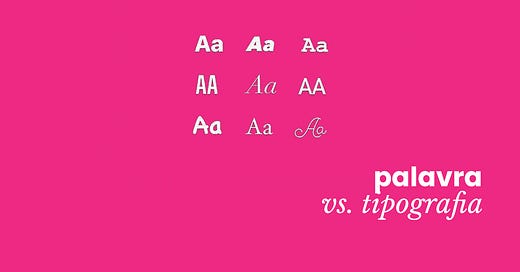
#63 palavra vs. tipografia
quando dois aspectos essenciais do texto são tensionados | tempo de leitura: 7 minutos
oie, seja bem vinde a mais uma edição da makers gonna make. a semente da edição de hoje foi plantada na minha cabeça em 2017, quando participei de um curso de escrita criativa e o professor contou uma anedota meio controversa sobre o design de um livro pela editora Cosac Naify. a história voltou num estalo na semana passada enquanto eu lia Design Gráfico: Uma história concisa, de Richard Hollis; e a partir daí fui ligando os pontos. o que está envolvido na relação - às vezes tensa - entre palavra e tipografia?
🔡 Tipografia para reforçar a mensagem
Estamos acostumados a usar sinais visuais para indicar nuances que achamos que faltam nas nossas palavras quando digitamos na internet: os emojis são o maior exemplo disso. Mas com a comunicação acontecendo cada vez mais através de layouts de posts ou texto aplicado sobre vídeo - e menos em textos corridos, como esse - isso se estendeu também para o campo da tipografia (não que nesse texto não haja tipografia, mas eu certamente conto com menos recursos no Substack e no e-mail do que em outros espaços virtuais).
Pode parecer bobo, mas eu acho que nos últimos anos os stories do Instagram se tornaram um espaço de exploração tipográfica. Cada vez que uma pessoa, designer ou não, posta uma foto acompanhada de texto, ela pode escolher entre as nove opções de tipografia que o Instagram oferece, além de algumas opções de animação (!) e infinitas possibilidades de cores. Já vi muita gente clicar em todas as opções e decidir qual prefere no feeling, mas esse não deixa de ser um trabalho de adequação de tom tipográfico para e mensagem textual.
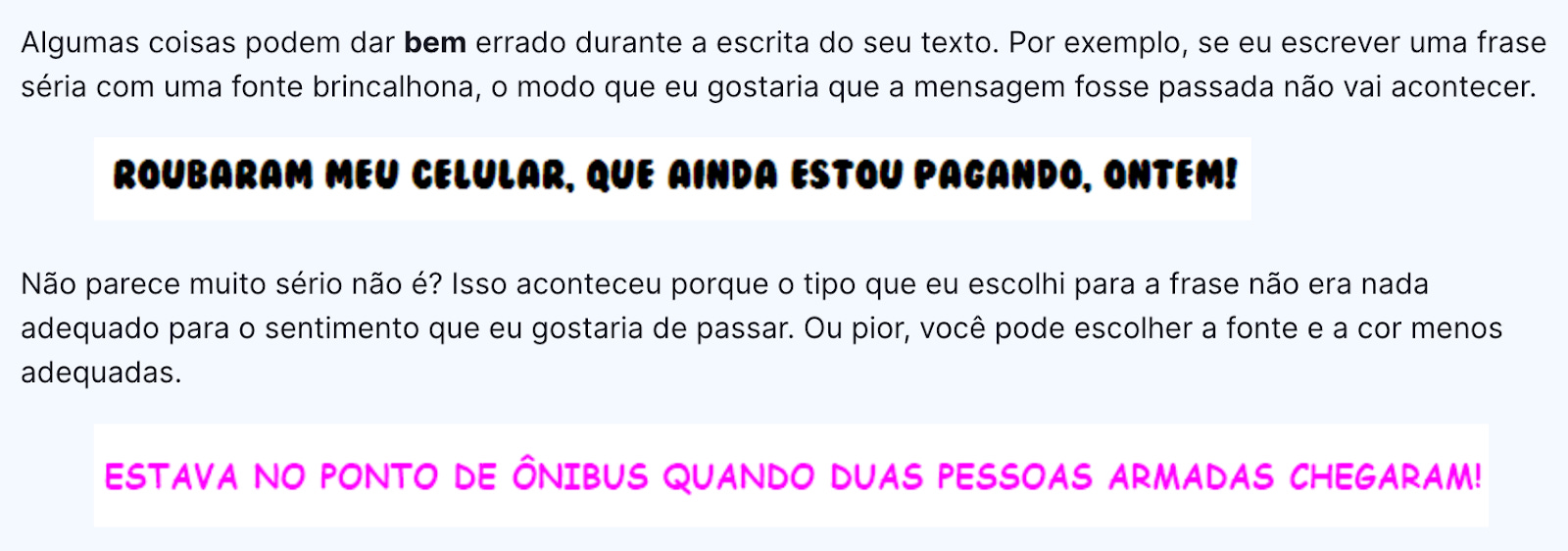
Essa relação entre forma e conteúdo não é recente: a formação clássica em design gráfico nos ensina que a aparência de uma palavra tem tanto ou mais força quanto o seu significado. Um argumento comum para engrandecer os feitos tipográficos é que a tipografia não é só importante, mas necessária para suprir uma espécie de deficiência da palavra impressa (ou, hoje, a palavra digitada). Como escreve Richard Hollis em Design Gráfico: Uma história concisa:
“A palavra, quando impressa, na forma de registro da fala, perde uma extensa variedade de expressões e inflexões. Os designers gráficos contemporâneos (especialmente seus precursores, os futuristas) têm tentado romper essa limitação. Ampliando ou reduzindo os tamanhos, os pesos e a posição das letras, seu tipografismo consegue dar voz ao texto. Instintivamente, existe um anseio não só de transmitir a mensagem, mas também de dar a ela uma expressão única.”
Essa mesma noção está difundida até nos guias mais básicos de tipografia disponíveis online. Um bom exemplo é esse artigo da Rock Content: Tipografia: como usar um dos pilares do Design Gráfico a seu favor, em que o autor usa uma série de anedotas visuais para ilustrar seu ponto:
“Por serem a base da comunicação escrita, os tipos precisam ser muito bem trabalhados para serem adequados à mensagem que você deseja passar e o modo como você deseja passar essa mensagem.”
🧪 Estudos e hipóteses
As “impressões” apresentadas sobre tipografia até aqui já foram testadas algumas vezes. No artigo How typography impacts your mood (que é um trecho retirado do livro Why Fonts Matter, da mesma autora), Sarah Hyndman escreve:
“Há um paralelo entre o que vivenciamos no mundo físico e como isso influencia a nossa interpretação das formas dos tipos de letra. O tipo pode ser visto como um espelho das emoções que demonstramos no mundo real por meio de nossas expressões faciais e gestos.”
A partir de um estudo realizado por Poffenberger and Barrows em 1933, que explorou como formas simples e linhas poderiam comunicar emoções, Sarah busca por correspondentes tipográficos para cada emoção: uma tipografia com ângulos pontudos e direcionados para cima pode traduzir raiva e agitação, enquanto outra com curvas suaves e equilibradas sugere felicidade e amabilidade.
Ela também cita o estudo Emotional and Persuasive Perception of Fonts, de 2008, no qual os psicólogos Samuel Juni e Julie Gross distribuíram o mesmo artigo satírico do New York Times para 102 estudantes, alguns em Arial e outros Times New Roman. Após a leitura, os estudantes classificaram o texto a partir de uma lista de adjetivos pré-determinada, e aqueles que leram o artigo em Times New Roman o classificaram como mais “engraçado” e “raivoso” (ou seja, mais intenso no tom satírico).
É bem possível que essas percepções variem regionalmente, seja por conta da língua, do alfabeto utilizado ou mesmo da cultura visual de cada sociedade; mas ainda sim esses testes associativos demonstram que a escolha tipográfica pode reforçar ou enfraquecer um tom específico no texto.
📖 E quando a mensagem não quer ser reforçada pelo design?
Como uma designer que escreve, eu frequentemente penso na forma das palavras que escolho. É comum que eu já escreva já pensando em como as frases vão estar posicionadas, em qual tipo de papel serão impressas, quais cores e técnicas de impressão vou usar. Mas sempre me lembro de uma anedota que um professor me contou em um curso de escrita criativa:
obrigada por ler até aqui! na edição passada o Thiago Ambrósio Lage me disse que têm textos que são mais resposta e outros que são mais pergunta. acho que esse é mais pergunta, um convite pra reflexão: estamos subestimando a capacidade das palavras de transmitir mensagens completas? como a tipografia pode ser uma aliada sem passar por cima do conteúdo? como sempre, fique a vontade para responder esse e-mail se quiser conversar, compartilhar algo ou até mesmo criticar algum ponto da newsletter. ah, e se você conhece alguém que pode gostar desse texto, compartilhe a newsletter :)